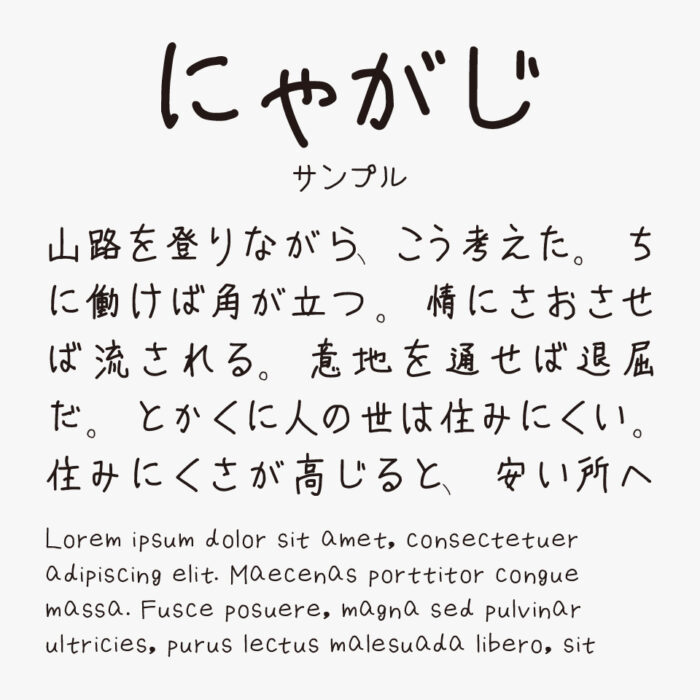
にゃがじ
にゃがじフォントは、Vtuberとし活動されている星娘さんによるゆるやかな手書き風の丸みに癒される、親しみやすい手書きフォントです。
線の太さにわずかな強弱があり、まるでノートにペンで書いたような、リアルなタッチが印象な手書き文字です。
丸みを活かした湿地が特徴で、「が」や「じ」の濁点などにもリズムがあり、可愛らしい動きのある表情がとてもステキなフォントです。
収録文字は、漢字(JIS第一水準漢字まで、JIS第二,第三水準も一部収録)・ひらがな・カタカナ・アルファベット・数字・記号が収録されています。